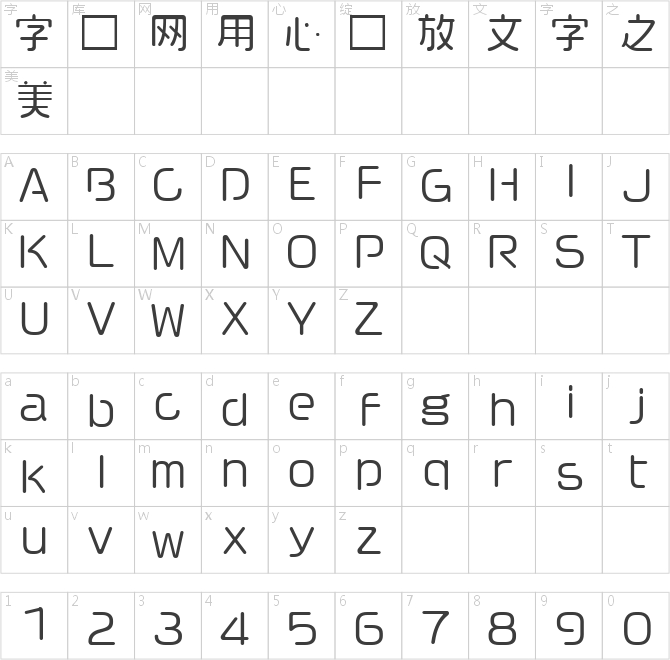
TruTrueMegaMaru-M 详情页
字体名称: TruTrue
字体类型: 日文字体
TruTrueMegaMaru-M
TruTrueMegaMaru-M字体视觉研究所メガ丸字库是一款让人赏心悦目、百看不厌的日文字体,适合各类广告和产品包装设计应用,字体大小4.45MB,格式为TTF字体,上传用户是ㄚòひ慬偶鰢,作者/版权方为视觉研究所